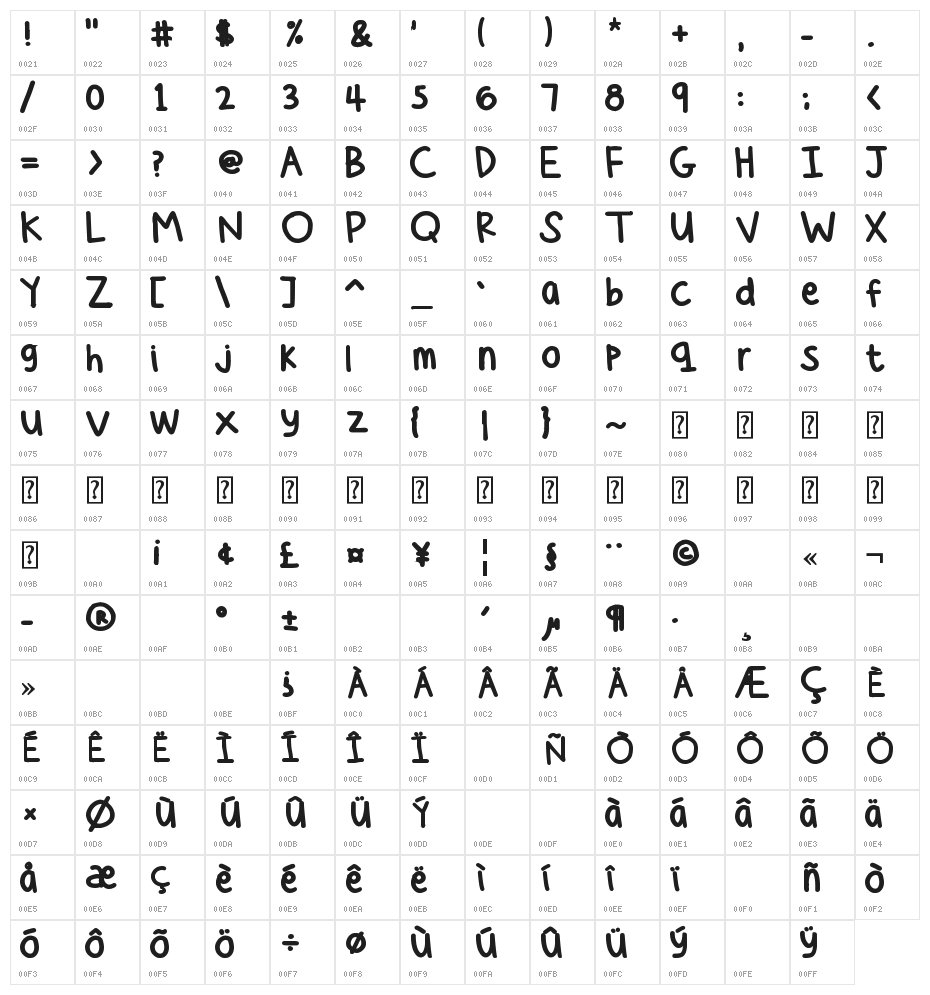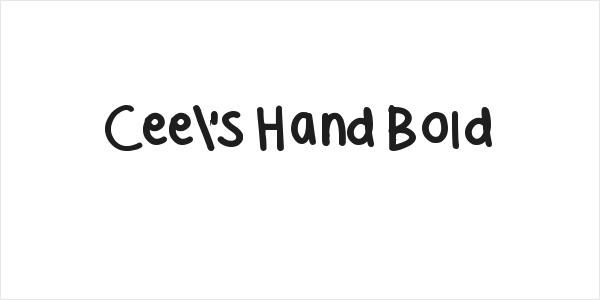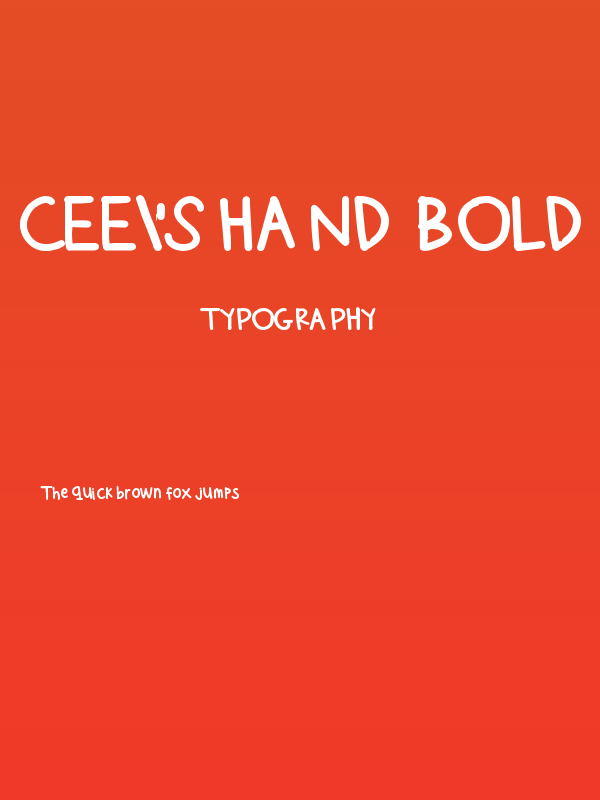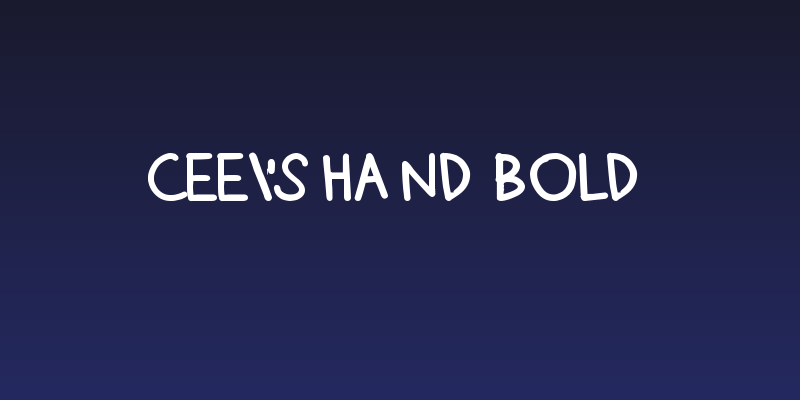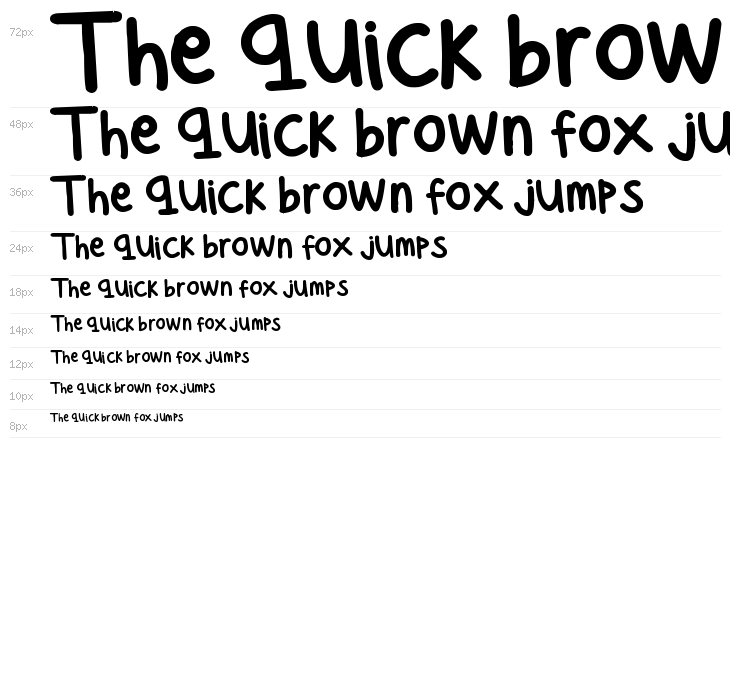
Cee's Hand Bold Font
✎ Handwritten
| समग्र शैली | Casual, Playful |
| उपयोग का मामला | Headlines, Logos, Informal Text |
| सुझाए गए प्रोजेक्ट | Ideal for children's books, greeting cards, casual branding, and social media graphics. |